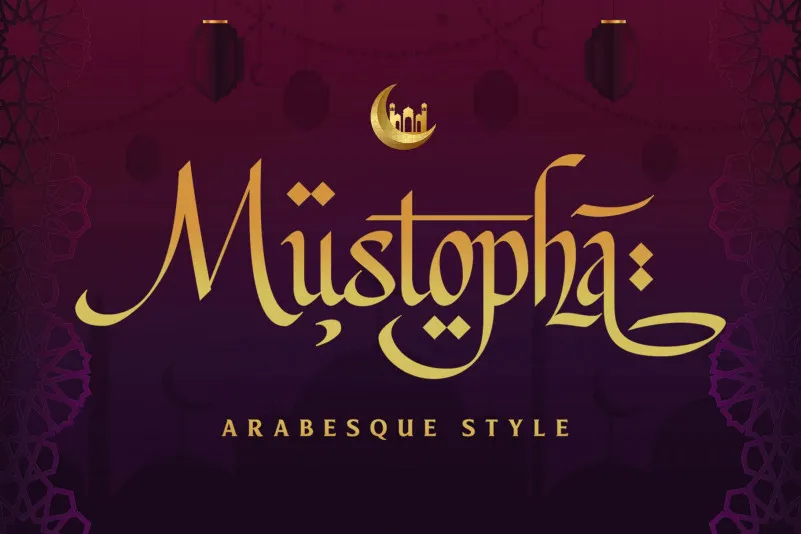
Mustopha Font – Download Grátis
A fonte ‘Mustopha Font’ é uma sugestão inspirada no alfabeto árabe e na arte do xilográfico, trazendo alternativas e recursos multilingue para uma experiência de escrita ainda mais rica e variada. Esta fonte foi projetada pelo Arterfak Project, que combina a estética humanista da tipografia Carolingiana com o ar desenhado dos alfabetos árabes. As letras são criadas através do encontro entre essas duas influências, resultando em uma fonte que transmite um toque de elegância e sofisticação sem se perder na expressividade única do xilogrifo árabe. Com alternativas em cada letra, a ‘Mustopha Font’ é ideal para designers buscando uma mistura entre a elegância arábica e o charme humanista da tipografia clássica. Um convite para explorar e integrar estilos tão peculiares como o desenhado do árabe em suas criações digitais.